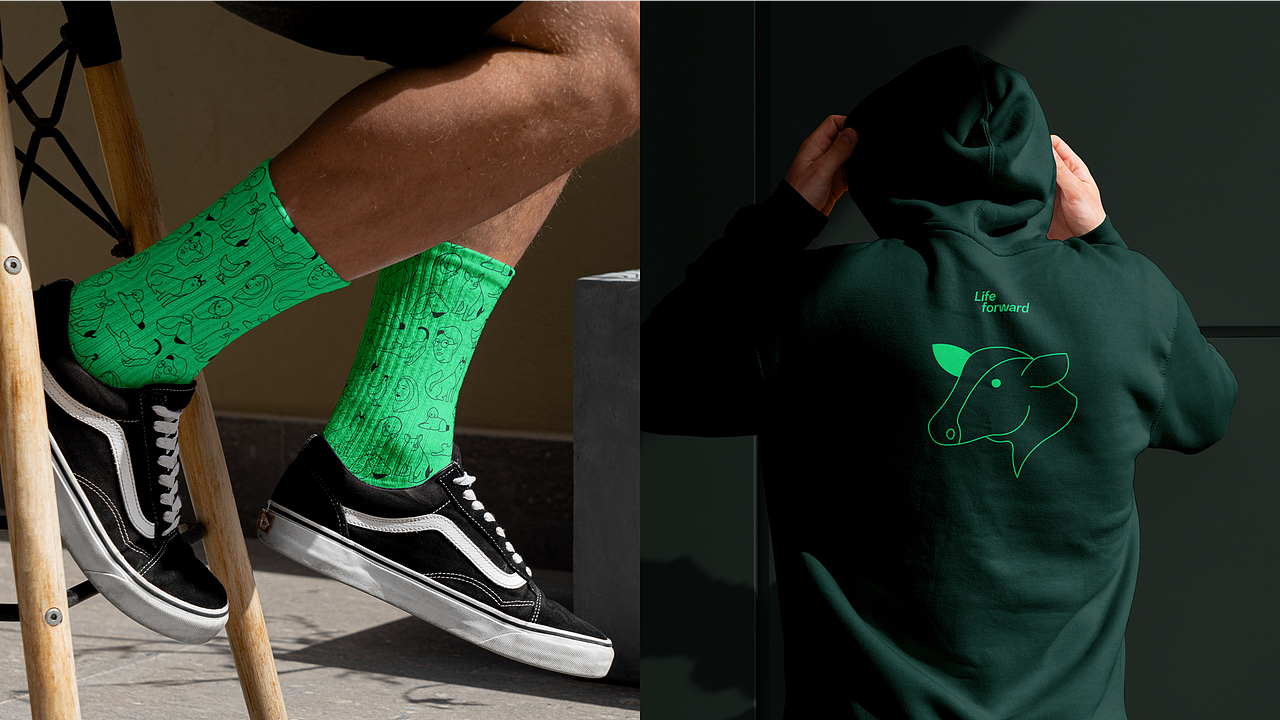
这家名字“很难读”的医药巨头,定制字体怎么做?
作为一家百年企业,勃林格殷格翰致力于改变全球人类和动物的生活。去年,这家德国医药公司也经历了自身转型,其中包括由世界知名品牌咨询公司 Interbrand 牵头、蒙纳作为字体合作伙伴进行的品牌重塑。蒙纳为其定制的可变字体在其品牌蜕变的过程中发挥关键作用。
勃林格殷格翰医药公司面临的独特挑战,便是找到一款大到广告牌,小到药品手册,能在各种尺寸的排版中保持一致形象的字体。
于是 Boehringer Forward 诞生了。这款全面的定制可变字体横跨各种尺寸以及语言,传达属于勃林格殷格翰坚定乐观的品牌气质,呼应全新品牌主张:Life Forward。
灵活:可变、不再局限
品牌重塑通常需要更换字体。当然,企业规模越大,转型就越复杂,但尽管任务繁杂,这也为提升品牌可靠性提供了一个真正的机会。对于一家全球医药公司而言,字体更换面临着更大的挑战 —— 药物管理本身便存在风险,在关键时刻药物标签和手册上文字的易认性可以说是生命攸关。
Boehringer Forward 的首要特征便是灵活可变。可变字体比大多数人想象得更为强大,于 2016 年推出后,在过去几年逐渐兴起。可变字体是指将字体设计格式整合到单个字体文件中,让用户可以灵活地调整字号、字重和斜度,从而得到一款易于使用、轻松排版的字体家族,即便在极小字号也能清晰易读。
Interbrand 的 Eva Olk 形容使用可变字体的感受「就像在把玩一个新玩具」,这个过程本身就「非常自由」。可变字体不再局限于固定的斜度和字重,而是以全新方式为用户提供灵活性、控制力和自由度。Eva 补充道:“这不仅有趣,更意义非凡。这对品牌运作的改善,将为其积累更多用于创新的资源。”
独特:细节拓展的视觉语言
为和勃林格殷格翰的品牌主张及战略产生紧密共鸣,Boehringer Forward 富含独特细节,为其拓展视觉语言,展现推动医疗行业发展的人性化特征。
首先便是视觉字号的调整。视觉字号考虑到不同使用环境中字号的差异,关注字符形状、字间距的细微差异会如何影响易认性与风格呈现,因此 Boehringer Forward 包含了标题(Dispaly)、正文(Text)、微型(Micro)三种视觉字号,以适应从广告屏幕到药品手册等各类触点。
A、W、y 等字母体现了有趣的切角与形状,而小写字母 l 和开放的字怀适用于正文和微型视觉字号,有助于提高易认性。—— Emilios Theofanous,蒙纳字体创意总监
就字体本身也有不少趣味,从细微瞬间中呈现意义,例如精准的切角、油墨陷印以及突出创新个性的细节。可以注意到大写字母 A、W、B 以及小写字母 y 和 l,它们的造型都尤为乐观洋溢。
近看,这款字体的细节自成故事;远看,字体与品牌色调、图像、布局等其他关键视觉元素也格外协调。
普适:更多语言,走得更远
所有跨国企业都面临共同的字体挑战,即在不同语言中实现视觉声音的一致。虽然勃林格殷格翰总部位于德国,但其业务遍布全球,因此蒙纳设计团队在字体创意总监 Emilios Theofanous 的指导下,首先确定了拉丁字符的设计。
随后,蒙纳的字体专家以及创意合作伙伴们协作拓展,与大曲都市(Toshi Omagari)完成了阿拉伯语,与 Parachute 扩展了希腊语,与 Cadson Demark 敲定了泰语。通过这一合作方式,特定语言方面的字体设计专家能够发挥其专业知识,为最终呈现的多语种字符集打下坚实基础。
因此 Boehringer Forward 具有极强的内聚力,能够克服地理和语言带来的品牌挑战,将品牌成功地扩展到国界之外;对于超过 5 万名员工而言,这也是一份尤为重要的内部资产。
Boehringer Forward 解决了排版问题,提供了所需的语言支持,同时坚持了品牌的语气,设计现代而多变,兼具功能性和品牌价值。—— Emilios Theofanous,蒙纳字体创意总监
实用:让字体产生连锁反应
在设计过程中,某些字体元素从一开始就将易认性放在首位,这也有助于提高可及性。例如,小写字母 l 上的小曲线是经过反复测试推敲后决定的,目的是将其与大写字母 i 区分开来,同时又符合美学要求。Emilios 指出:“设计要考虑到易认性,以及因健康和年龄而异的视觉能力,这一点非常重要。”
当字体中的品牌性和功能性巧妙结合,将有助于消费者对企业建立信任。对于医药公司而言,这将帮助他们积累更多、创造更多、实现更多。
展望
蒙纳与勃林格殷格翰的合作彰显了定制可变字体如何解决医药行业复杂的排版难题。通过利用蒙纳的专业知识和技术,勃林格殷格翰不仅增强了品牌一致性和沟通清晰度,还实现了更高的运营效率和监管合规。在现代品牌塑造和传播战略中,字体总能以巧制胜,化繁为简,为企业带来更多变革。